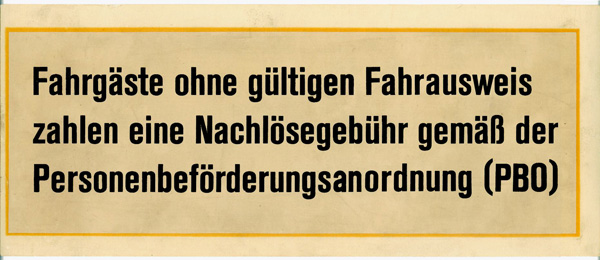
Und wieder wird eine Schrift gesucht (DDR??) ...
die diesmal von mir gesuchte Schrift wurde so in Ostberlin vor der Wende auf Abziehbildern verwendet.
Sie sieht mir eigentlich nicht wie eine DDR-typische Schrift aus.
Es war ja sonst fast "alles" in Drescher Grotesk oder ähnlichen Schriften gedruckt.
Ich konnte mir selbst helfen. Über https://www.myfonts.com/WhatTheFont konnte ich ermitteln, daß die Schrift auch zur "Akzidenz Grotesk" gehört.
Lustig, irgendwie kam sie mir bekannt vor. Aber da ich sie ja für meine Zwecke angepaßt hatte, hab ich es nicht mehr gleich erkannt.
Habe es gleich mal ausprobiert, da ich die Berthold Akzidenz Grotesk habe.
Es ist Condensed Fett:
Hat sich also erledigt :-)
Sie steht auf einem vom Braunkohleruß vergilbten Untergrund.
Aha. Klar, vergilbtes Papier oder verblichene Farben gab und gibt es im Westen natürlich nicht ... warum fällt mir sowas nur immer in Österreich auf?
Aber was hat das mit der Schrift zu tun? Ich würde wirklich gerne wissen, was denn nun das "Typische an DDR-Schrift" sein sollte oder könnte ...
Müssen doch die Verfechter solcher Thesen irgendwie erklären können. Oder langt es dazu nicht?
Nun mach mal keine Staatsaffäre draus. Hier hat niemand »Thesen verfochten«.
So schwer war der obige Satz ja auch nicht zu verstehen. Dass es AN DDR-Schriften etwas typisches gäbe, hast du gerade geschrieben. Sanvean schrieb nur von »typischen DDR-Schriften« - also den in DDR typischerweise verwendeten Schriften. Deren Zahl war ja überschaubar, da es keinen freien Wettbewerb unter Schriftanbietern gab. Und so gab es also eine Handvoll typische Schriften, die in weiter Verwendung waren. Und eine schmale Akzidenz Grotesk gehörte nicht dazu. Sie sieht also nicht wie eine der »typischen DDR-Schriften« aus. Mehr steht doch da nicht. Bestimmte Regionen und/oder Zeitabschnitte mit bestimmten dafür typischen Schriften zu verbinden, ist doch nichts außergewöhnliches.
typische DDR-schriften sind halt die schriften die man damals™ oft gesehen hat.
dazu zähle ich unter anderem diesen gill-verschnitt von den verkehrschildern (die gill war sowieso oft vertreten, siehe NBI),
dann diese typische schrift von den plastikschildern, pachulke hatte die schonmal gesucht und wir hatten auch herausgefunden wie dies hieß. ich glaube das war die folio. folio wurde auch viel via typofixbögen vertrieben, ähnlich wie im westen die letrasetbögen.
ansonsten sind für mich aber auch Liberta, Super Grotesk, Splendor und Minima von Typoart typische vertreter dieses genres. Vorallem die Super Grotesk war meine erste bleischrift (neben der Mimosa) mit der ich damals in kontakt gekommen bin. ich denke jeder bürger aus der ehemaligen DDR kann ein bild im kopf hervorrufen wenn man ihn darauf anspricht. sicherlich, es gibt nicht die DDR-schrift – wenn man dies in bezug auf die form sieht, denn es gab ja verschiedene stile und formen über die jahre hinweg, vom bauhaus bis zu pinselschriften von schildermachern etc. war da alles vertreten.
Nun mach mal keine Staatsaffäre draus.
Also echt! Da fasse ich mir ja an den Kopf, was mir hier unterschwellig unterstellt wird. :-(
Sanvean schrieb nur von »typischen DDR-Schriften« - also den in DDR typischerweise verwendeten Schriften. [...] Und eine schmale Akzidenz Grotesk gehörte nicht dazu. Sie sieht also nicht wie eine der »typischen DDR-Schriften« aus. Mehr steht doch da nicht.
Danke - Applaus! Genau so hatte ich es gemeint, und genau so werden es 99 % auch verstanden haben ;-)
Also echt! Da fasse ich mir ja an den Kopf, was mir hier unterschwellig unterstellt wird. :-(
Das war Ralf Antwort an gutenberger, nicht an dich ;-)
... ich denke jeder bürger aus der ehemaligen DDR kann ein bild im kopf hervorrufen wenn man ihn darauf anspricht...
Auch wir anderen, die wir dank des irrealen Umtauschkurses importierte "gesetzte" Bücher für ein Spottgeld kaufen konnten  :ilovetype:
Die Kehrseite dieses für euch so tollen Schnäppchenumtauschkurses war natürlich, dass DDR-Rentner auf Westbesuch das Äquivalent mehrerer Monatseinkommen aufbringen mussten, um nicht mir leeren Händen nach Hause fahren zu müssen und wenigstens ein paar billige Geschenke für ihre Enkel mitbringen zu können.
Aha. Ich hab mich gar nicht angesprochen gefühlt, weil ich da gar keine Staatsaffäre sehe. Mich hat nur die Frage interessiert, was typisch an einer DDR-Schrift wäre bzw. sein könnte und diese Braunkohlenbemerkung aus dem blauweißen Dunstkreis fand ich weder besonders witzig noch diesbezüglich hilfreich ...
So isses. Bei mir hängt dieses Schild über der Tür, das meine Schwiegereltern geschickt haben¹, eben weil es nach ihrer Wahrnehmung ein typisch olles DDR-Schild ist:
1. nachdem ein ungebetener »Gast« durch die amerikavorstadttypisch unverschlossene Haustür spaziert war
… weil es nach ihrer Wahrnehmung ein typisch olles DDR-Schild ist …
Na klar, wenn Dewag Signograph, Druckgenehmigungsnummer und EVP-Preis draufsteht, wäre es schwierig, das nicht als DDR-typisch wahrzunehmen — relativ unabhängig von der Typographie.